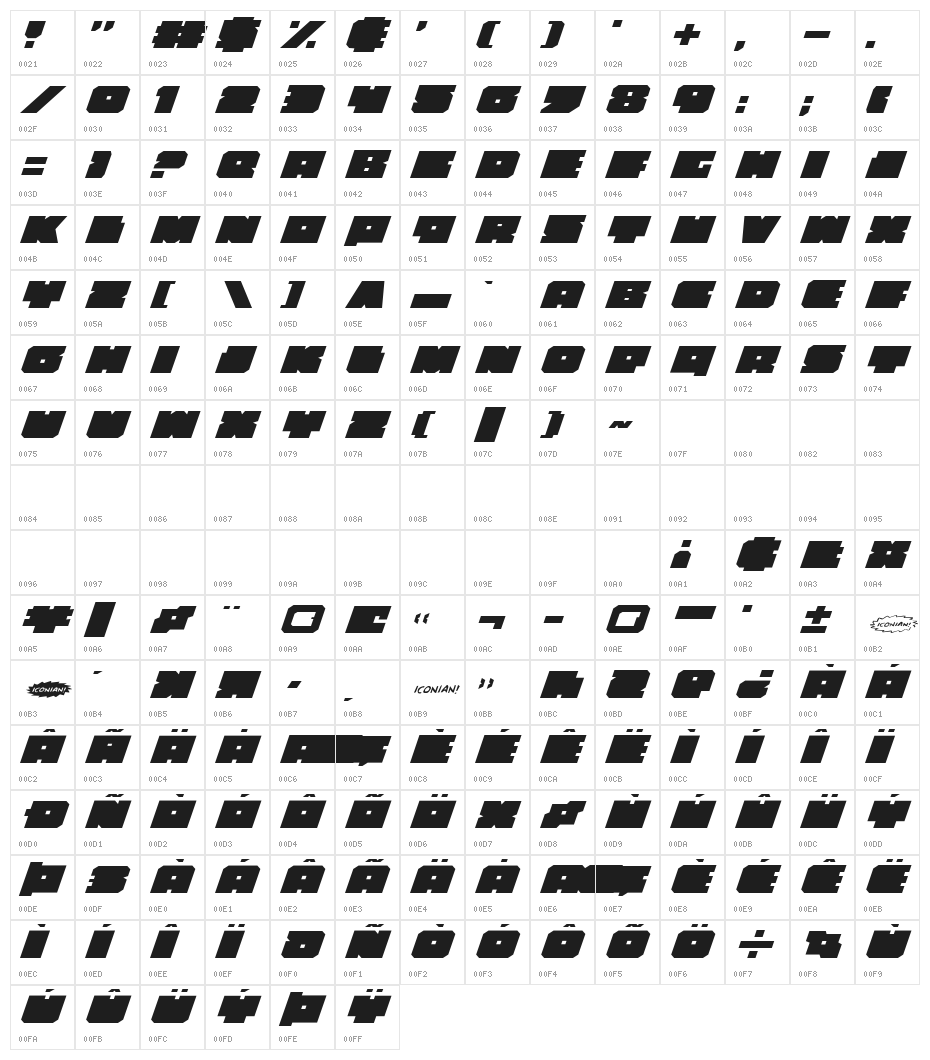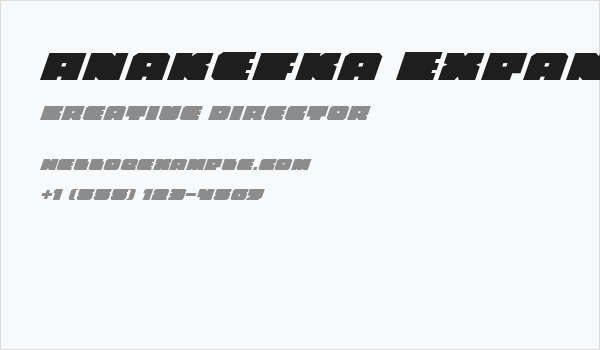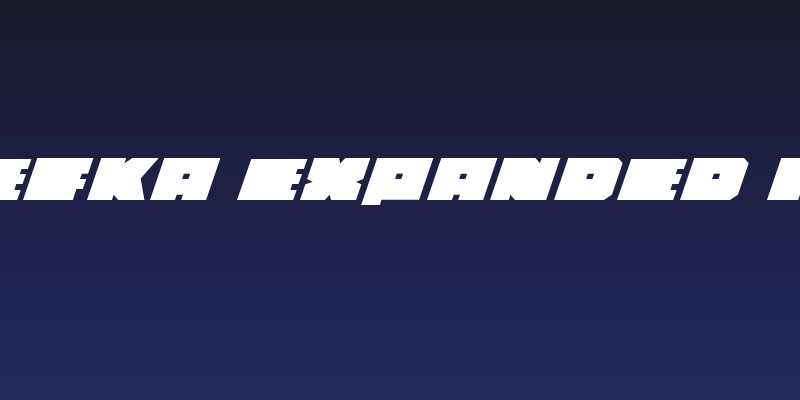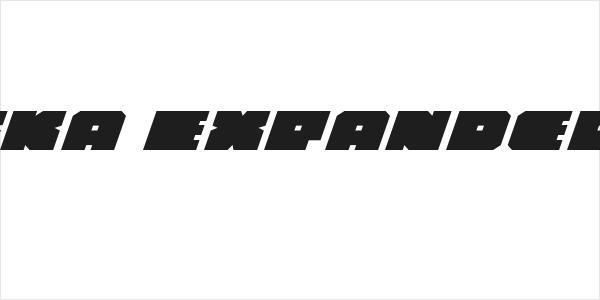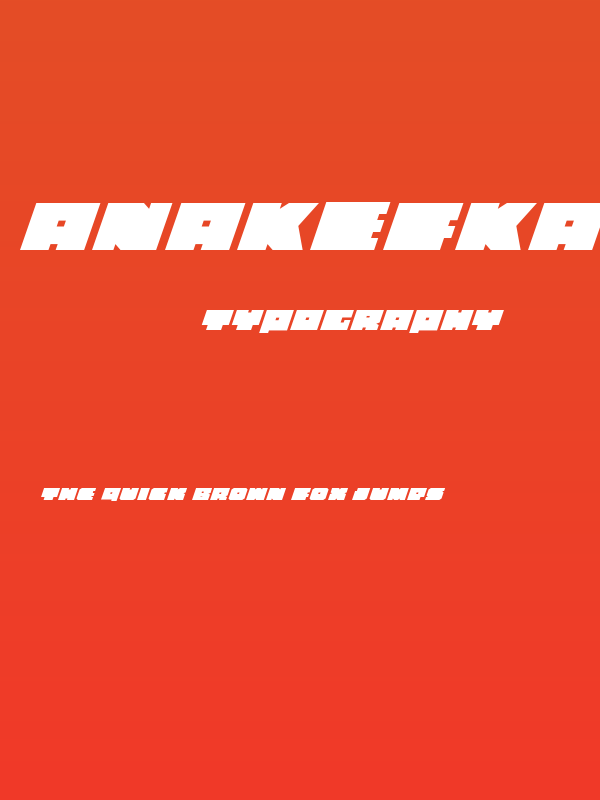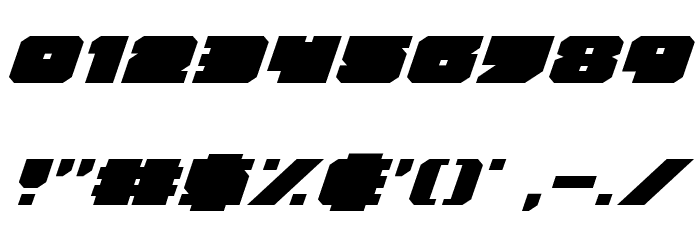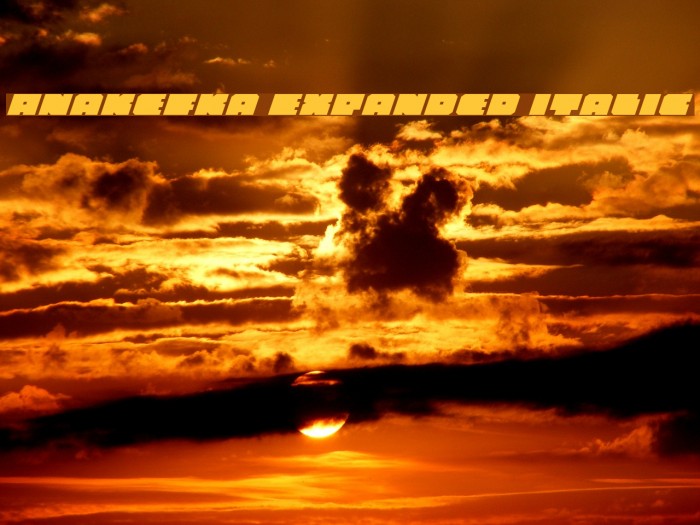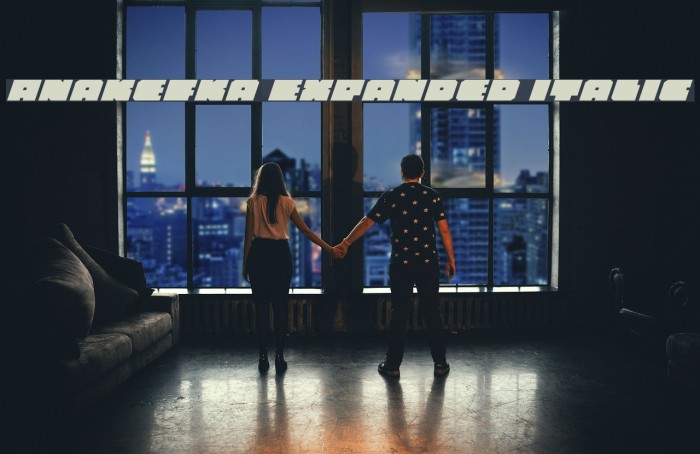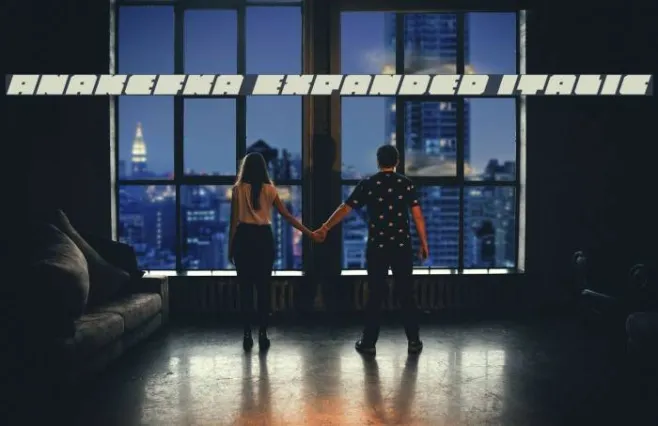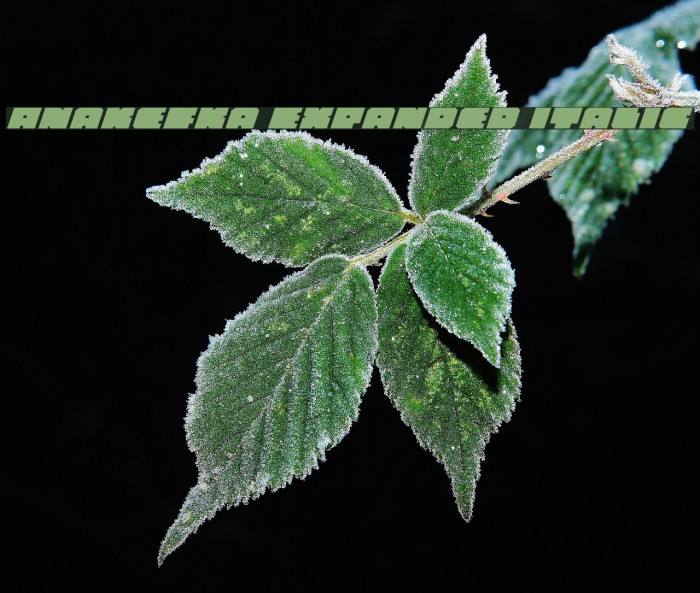
Anakefka Expanded Italic Font
| Style général | Futuristic, Edgy |
| Projets proposés | Ideal for sci-fi themed posters, video game titles, and branding that requires a modern and bold aesthetic. |